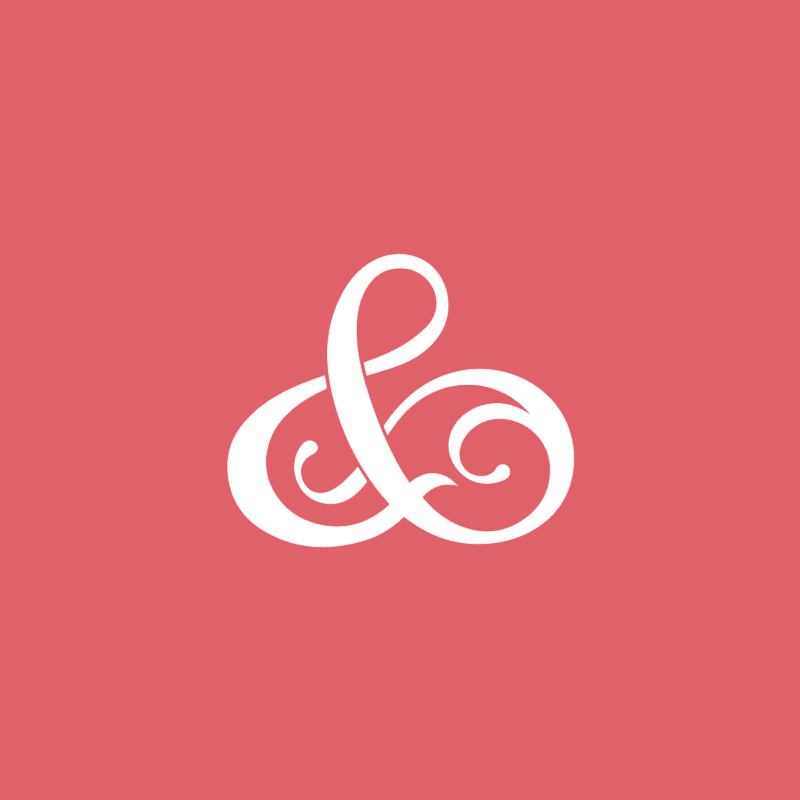
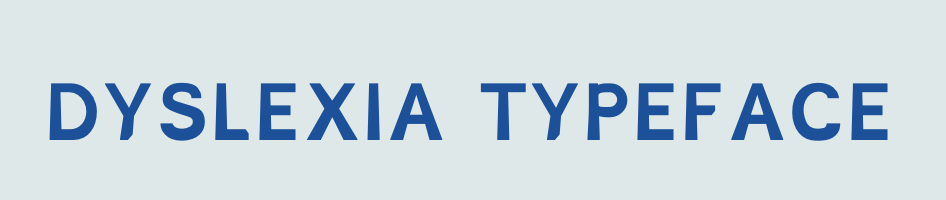
הידעת? פונט ״Dyslexia״ הוא פונט שנוצר במיוחד עבור דיסלקטים ועוזר להם לקרוא בקלות.
הפונט נוצר על ידי המעצב הגרפי ההולנדי כריסטיאן בוהר.
הפונט כולל שינויים עדינים בצורות האותיות המקלים על ההבחנה ביניהן, ומפחיתים את הסבירות לבלבול והיפוכי אותיות.
הוא מבוסס מחקר מדעי על דיסלקציה, והעיצוב שלו משלב תכונות כמו חלקים תחתונים כבדים יותר, פתחים גדולים יותר וגבהים משתנים של אותיות כדי לשפר את הקריאות עבור קוראים דיסלקטים.
הוכח כי ״פונט Dyslexia״ משפר את מהירות הקריאה והדיוק עבור אנשים עם דיסלקציה, והוא נמצאת כיום בשימוש נרחב בחומרים חינוכיים ובהקשרים אחרים שבהם ניתן למצוא קוראים דיסלקטים.
לטיפוגרפיה יכולה להיות השפעה כל כך מוחשית על חייהם של אנשים, ואני מאמינה שכמעצבים, חשוב לקחת בחשבון את הצרכים המגוונים של קהלים שונים כשאנחנו יוצרים טיפוגרפיה ואלמנטים עיצוביים אחרים. על ידי מודעות לאתגרים הייחודיים איתם מתמודדות קבוצות שונות של אנשים, נוכל ליצור עיצובים מכילים ויעילים יותר שבאמת עושים את ההבדל.
הידעת? סימן ה-@ ייצג בימי הבייניים את המילה ״אמפורה״ שהייתה יחידת מדידה לכימות סחורות כמו דגן ויין
סמל ה-"@" הוא אחד הסמלים הנפוצים ביותר בתקשורת המודרנית, המופיע בכתובות דוא"ל, ידיות של מדיה חברתית ובהקשרים מקוונים ולא מקוונים אחרים. בעוד שאנשים רבים עשויים להניח שהסמל הומצא במיוחד לשימוש בכתובות דואר אלקטרוני, מקורותיו למעשה חוזרים הרבה יותר אחורה. כפי שהעובדה קובעת, כמה חוקרים טוענים שניתן לייחס לסמל "@" לרומא העתיקה, שם הוא שימש לייצג את יחידת המדידה המכונה "אמפורה". אמפורה הייתה סוג של מיכל המשמש להובלת סחורות כגון תבואה ויין, והסמל "@" שימש לציון מספר מסוים של מיכלים אלה. בעוד שהמקורות המדויקים של סמל ה"@" עדיין נתון לוויכוח בין היסטוריונים ובלשנים, מקובל כי לסמל יש היסטוריה ארוכה של שימוש מעשי במסחר ובמסחר. במאה ה-16, למשל, החלו סוחרים באירופה להשתמש בסמל כדרך קצרה לציון מחיר הסחורה, כאשר הסמל "@" מייצג את המילה "at"
כך השתמשו בסמל בשמך מאות השנים,
עד שבסופו של דבר אומץ על ידי המתכנת ריי טומלינסון (מי שיישם את תוכנת האימייל הראשונה) כדרך להפריד בין שם המשתמש ושם הדומיין בכתובות הדואר האלקטרוני.
כיום, סמל ה-"@" הוא חלק מהותי בתקשורת המודרנית, כאשר הרבגוניות והסתגלות שלו מאפשרות לו לקבל מגוון רחב של משמעויות ופונקציות בהקשרים שונים.
ההיסטוריה של סמל "@" היא עדות לדרכים שבהן שפה וסמלים מתפתחים לאורך זמן כדי לענות על הצרכים של תרבויות וקהילות שונות.
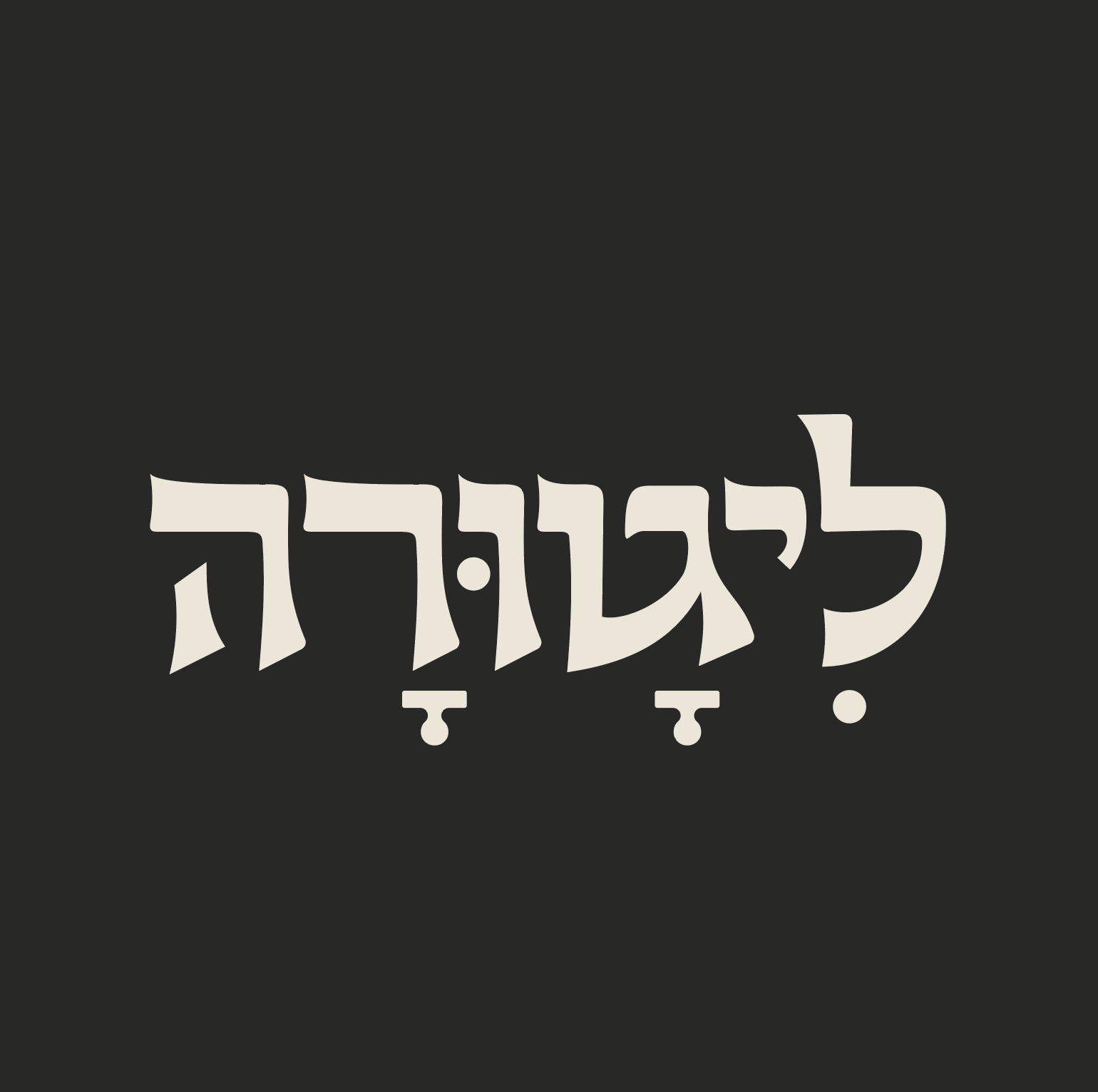
ליגטורות הן סמלים טיפוגרפיים ייחודיים שנוצרו על ידי חיבור של שתי אותיות או יותר יחד ליצירת גליף אחד בעלי קליגרפיה עברית. השימוש בהם היה נפוץ בעבר כשמכונות הדפוס היו ידניות והמקום על הנייר היה מוגבל. לדוגמה, בעבר, האותיות "f" ו-"i" חוברו יחד במילה "fifth"" כדי לחסוך במקום. היום אנחנו כבר לא זקוקים לליגוטורות בשביל להתמודד עם אתגרי דפוס. אבל בכל זאת הן עדיין מהוות חלק משמעותי ממערך הכלים של הטיפוגרף. למעשה, גופנים עכשוויים רבים כוללים ליגטורות כתכונה אופציונלית לשימוש עבור מעצבים.
בעבודות שלי אני מאוד אוהבת לשלב ליגטורות במגוון דרכים ליצירת עיצובים ייחודיים ובולטים מבחינה ויזואלית. אני מאמינה שהבנת הניואנסים של הטיפוגרפיה, כולל ליגטורות, חיונית ליצירת עבודת עיצוב משפיעה ובלתי נשכחת.
הידעת? האוסף הגדול בעולם של פונטים פיסיים מוחזק על ידי ארכיון טיפוסי האות בלונדון, שמכיל למעלה ממיליון פריטים, כולל קוביות עץ, מתכת וציוד דפוס
אוצר זה של היסטוריה טיפוגרפית הוא משאב רב ערך עבור מעצבים המעוניינים לחקור את ההיסטוריה העשירה של הטיפוגרפיה ולמצוא השראה לעבודה שלהם.
הספר הראשון בעולם שהודפס בדפוס מטלטלין היה תנ"ך גוטנברג, שהודפס על ידי יוהנס גוטנברג במאה ה-15. המצאה פורצת דרך זו חוללה מהפכה בתעשיית הדפוס וסללה את הדרך לייצור המוני של ספרים, עלונים וחומרים מודפסים אחרים.
לטיפוגרפיה יכולה להיות השפעה עמוקה על האופן שבו אנשים תופסים ויוצרים אינטראקציה עם טקסט. לדוגמה, מחקרים הראו ששימוש בגופן סריף יכול לשפר את הקריאה וההבנה, בעוד ששימוש בגופן sans-serif יכול לגרום לטקסט להיראות מודרני ויעיל יותר.
הפרקטיקה של פונט כתב יד הדפסת אותיות, הכוללת לחיצת סוג מתכת עם דיו על נייר, חווה עלייה מחודשת בפופולריות בקרב מעצבים ויוצרי הדפסה. טכניקת הדפסה מסורתית זו מציעה גישת מישוש מעשית לטיפוגרפיה המאפשרת למעצבים ליצור חומרים מודפסים ייחודיים ויפים עם תחושה של היסטוריה ואומנות.
הפונט הראשון שנוצר אי פעם אינו חלק מקבוצת פונטים בעברית, אלא "Blackletter" (גרמנית עתיקה), אשר שימש בכתבי יד ובספרים מימי הביניים.
"פונט" מתייחס לסט של אותיות בעלות משקל, גודל וסגנון מסוימים, בעוד "פונט-פייס" מתייחס לעיצוב האותיות באופן כללי. לדוגמה, Arial Bold 12pt הוא פונט, ו-Arial הוא פונט-פייס.